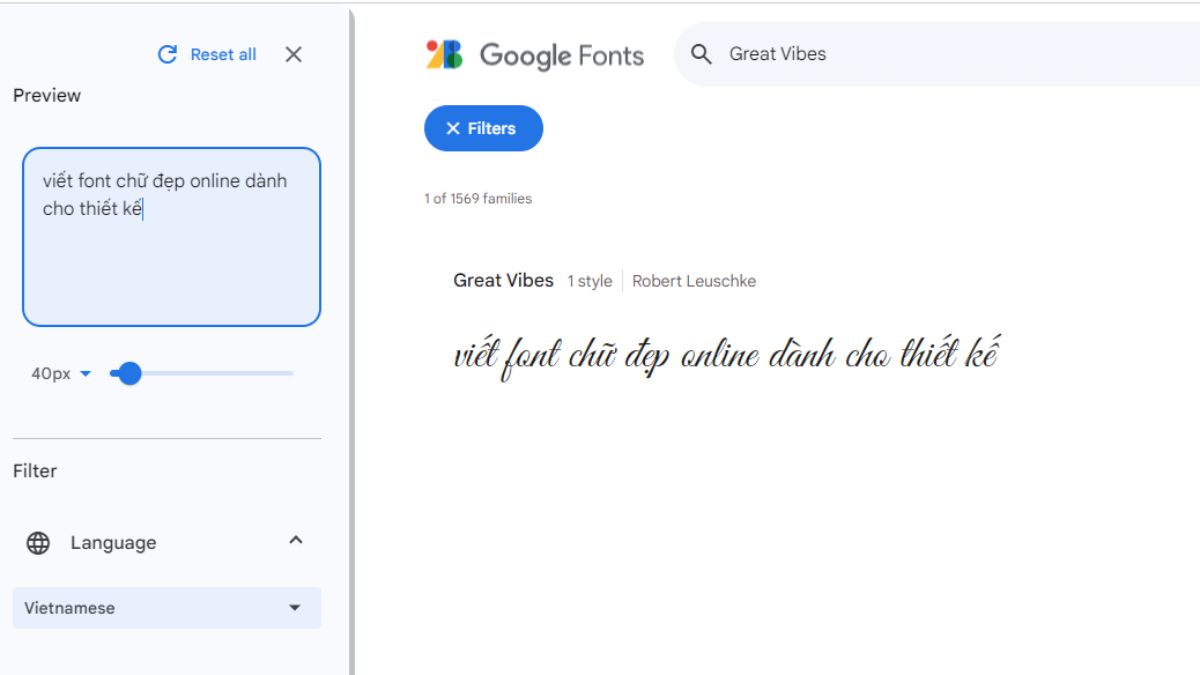
101+ Font chữ đẹp tiếng Việt được sử dụng nhiều nhất
Nếu bạn đang tìm kiếm những cách viết hay tạo kiểu font chữ đẹp online và chuyên dụng cho các mục đích như trang web, thiết kế đồ họa, hoặc cần tạo kiểu chữ đẹp để trang trí văn bản của mình. Hãy tham khảo bài viết này ngay, để giúp bạn tổng hợp các cách viết và tạo kiểu với những font chữ Tiếng Việt đẹp cho bảng chữ cái trên Facebook, Powerpoint, Tiktok, Word.
Tổng hợp các kiểu font chữ đẹp bảng chữ cái mới nhất
Dưới đây là một danh sách các kiểu viết font chữ đẹp online có thể sử dụng cho các nền tảng Facebook, TikTok, Powerpoint và Word, chữ Tiếng Việt được nhiều người dùng phổ biến với các mục đích khác nhau mà bạn có thể tham khảo ngay đây:
Font chữ đẹp Facebook
Có nhiều font chữ đẹp mà bạn có thể sử dụng cho Facebook. Tuy nhiên, hãy lưu ý rằng Facebook hỗ trợ một số font chữ cụ thể và không cho phép tùy chỉnh font chữ trong tất cả các phần của nền tảng. Dưới đây là một số font chữ phổ biến mà bạn có thể thử:
Arial: Đây là một font chữ đơn giản và dễ đọc. Nó là một font chữ thông dụng và được hỗ trợ trên hầu hết các nền tảng.
Times New Roman: Đây là một font chữ truyền thống, nổi tiếng và dễ đọc. Nó cũng là một lựa chọn phổ biến cho văn bản in ấn.
Verdana: Đây là một font chữ rõ ràng và dễ đọc, đặc biệt trên màn hình. Nó được thiết kế đặc biệt cho việc hiển thị trên web.
Calibri: Đây là một font chữ hiện đại, sạch sẽ và dễ đọc. Nó là một trong những font chữ mặc định trong Microsoft Office và được sử dụng phổ biến trên các nền tảng khác.
Georgia: Đây là một font chữ serif, có phông chữ thừa hưởng từ kiểu chữ thư pháp cổ điển. Nó thường được sử dụng cho các trang web và văn bản trên màn hình.
Font chữ đẹp Tiktok
Dưới đây là một số ứng dụng và trang web phổ biến mà bạn có thể sử dụng để tạo font chữ đẹp cho TikTok:
Font chữ đẹp trên Powerpoint
Trong Microsoft PowerPoint, bạn có thể sử dụng nhiều font chữ đẹp trên Powerpoint để tạo các trình chiếu ấn tượng. Dưới đây là một số font chữ phổ biến và đẹp mà bạn có thể thử:
Calibri: Đây là một font chữ hiện đại, sạch sẽ và dễ đọc. Nó là font chữ mặc định trong PowerPoint và thường được sử dụng cho các trình chiếu chuyên nghiệp.
Arial: Đây là một font chữ đơn giản, rõ ràng mà còn đẹp trên Powerpoint và phổ biến. Nó dễ đọc trên màn hình và rất linh hoạt trong các loại trình chiếu.
Helvetica: Đây là một font chữ truyền thống và phổ biến. Nó có thiết kế đơn giản, thanh lịch và dễ đọc, đặc biệt khi sử dụng cho các tiêu đề hoặc nội dung chính trong trình chiếu.
Garamond: Đây là một font chữ serif truyền thống, có phông chữ thư pháp cổ điển. Nó tạo ra một vẻ đẹp cổ điển và tinh tế cho các trình chiếu.
Futura: Đây là một font chữ hiện đại và đơn giản, đẹp trên Powerpoint, có thiết kế tương đối trực quan. Nó tạo ra một vẻ ngoại vi hiện đại và sự sáng tạo cho các trình chiếu.
Roboto: Đây là một font chữ sans-serif, phổ biến trên các nền tảng di động. Nó có thiết kế rõ ràng, dễ đọc và phù hợp cho các trình chiếu trực quan….
Font chữ đẹp trên Word
Trong Microsoft Word, bạn có thể sử dụng nhiều font chữ đẹp trên word để tạo tài liệu văn bản ấn tượng. Dưới đây là một số font chữ phổ biến mà bạn có thể thử:
Times New Roman: Đây là một font chữ truyền thống, phổ biến, đẹp trên word và dễ đọc. Nó thường được sử dụng cho các văn bản in ấn và đề cương.
Garamond: Đây là một font chữ serif truyền thống, có phông chữ thư pháp cổ điển. Nó tạo ra một vẻ đẹp cổ điển và tinh tế cho các văn bản.
Century Gothic: Đây là một font chữ sans-serif hiện đại, với thiết kế đơn giản, sắc nét và đẹp trên word. Nó thích hợp cho các văn bản với vẻ đẹp hiện đại và thanh lịch.
Verdana: Đây là một font chữ sans-serif dễ đọc trên màn hình. Nó có kích thước lớn hơn, làm cho văn bản trở nên rõ ràng và dễ nhìn…
Font chữ đẹp bảng chữ cái tiếng việt
Roboto: Đây là một font chữ sans-serif hiện đại, đẹp và phổ biến, có hỗ trợ cho tiếng Việt. Nó có thiết kế rõ ràng, đơn giản và dễ đọc trên mọi kích cỡ.
Montserrat: Đây là một font chữ sans-serif với thiết kế hiện đại và thanh lịch. Font chữ đẹp này có hỗ trợ tiếng Việt và đặc biệt phù hợp cho tiêu đề và văn bản nổi bật.
Open Sans: Đây là một font chữ sans-serif dễ đọc và linh hoạt, có hỗ trợ tiếng Việt. Nó thích hợp cho các loại tài liệu, từ bài viết cho đến trình bày thương mại.
Nunito: Đây là một font chữ sans-serif với kiểu dáng thoải mái và dễ đọc.Font chữ này có hỗ trợ cho tiếng Việt và thích hợp cho các tài liệu và thiết kế đa dạng hơn.